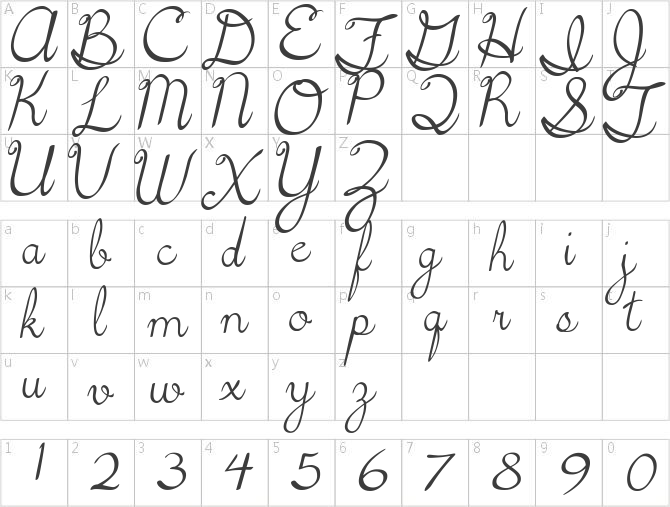
字体名称: 5thgrad
5thgradecursive-2-italic
5thgradecursive-2-italic介绍
5thgradecursive-2-italic字体字库是一款让人赏心悦目、百看不厌的英文字体,适合各类广告和产品包装设计应用,字体大小0.04MB,格式为ttf字体,上传用户是shiqiuping,作者/版权方为未知